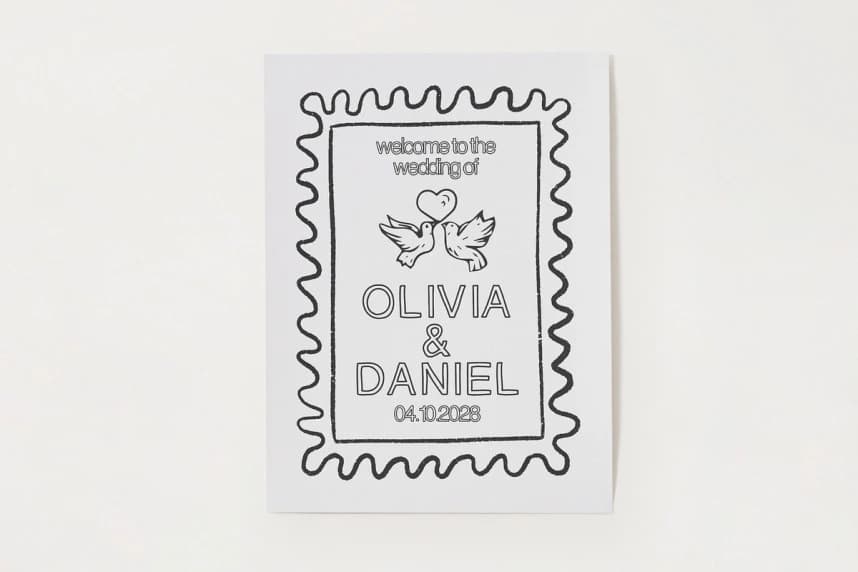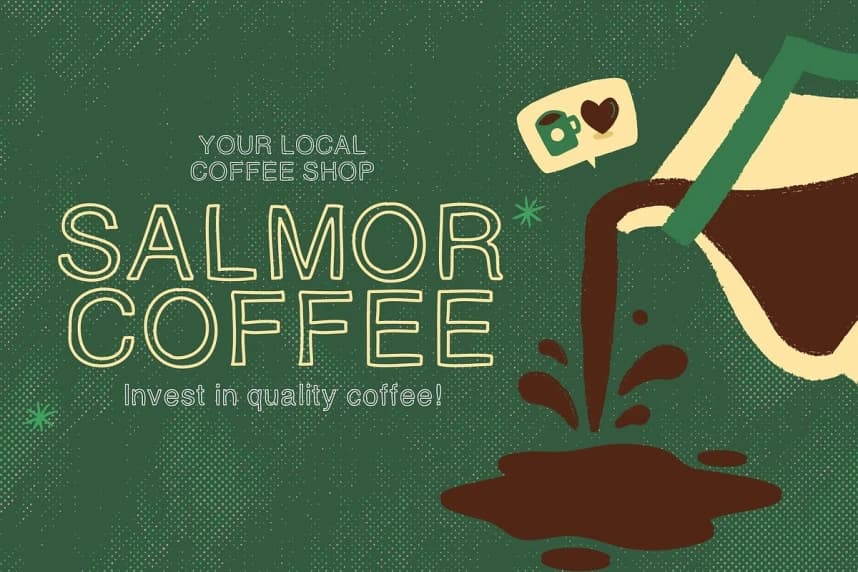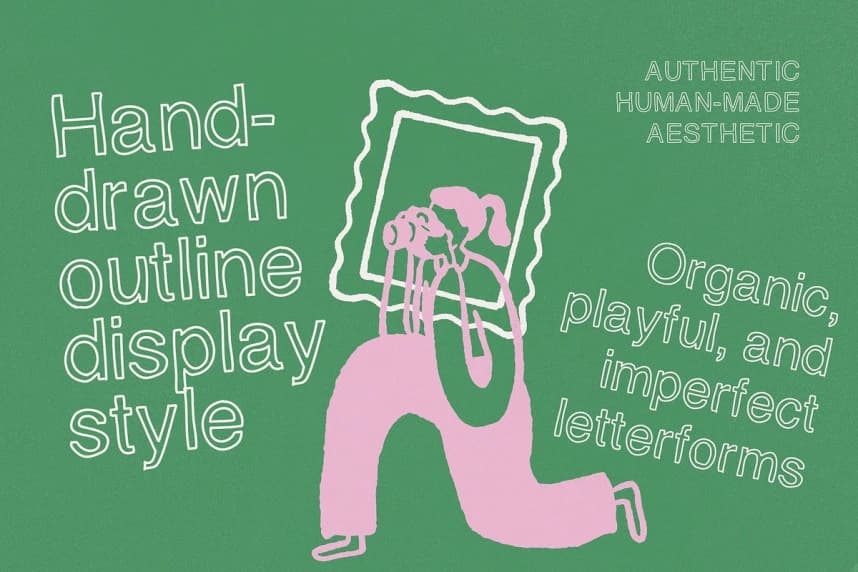
Happy Hollow Font
Happy Hallow Font, kişilik, çekicilik ve genç enerjiyle dolup taşan canlı bir el çizimi konturlu yazı tipidir. Kusurun güzelliğini kutlamak amacıyla tasarlanmış bu eğlenceli gösterim yazı tipi, organik çizgilere ve dengesiz detaylara yer vererek her harfe sıcak, otantik bir insan hissi kazandırır.
Happy Hallow Font, kişiliği, çekiciliği ve genç enerjiyle dolup taşan canlı el çizimi konturlu bir yazı tipidir. Kusurun güzelliğini kutlamak için tasarlanmış bu eğlenceli gösterim yazı tipi, organik çizgileri ve düzensiz ayrıntıları benimser; bu da her harfe sıcak, özgün ve insana özgü bir his verir.